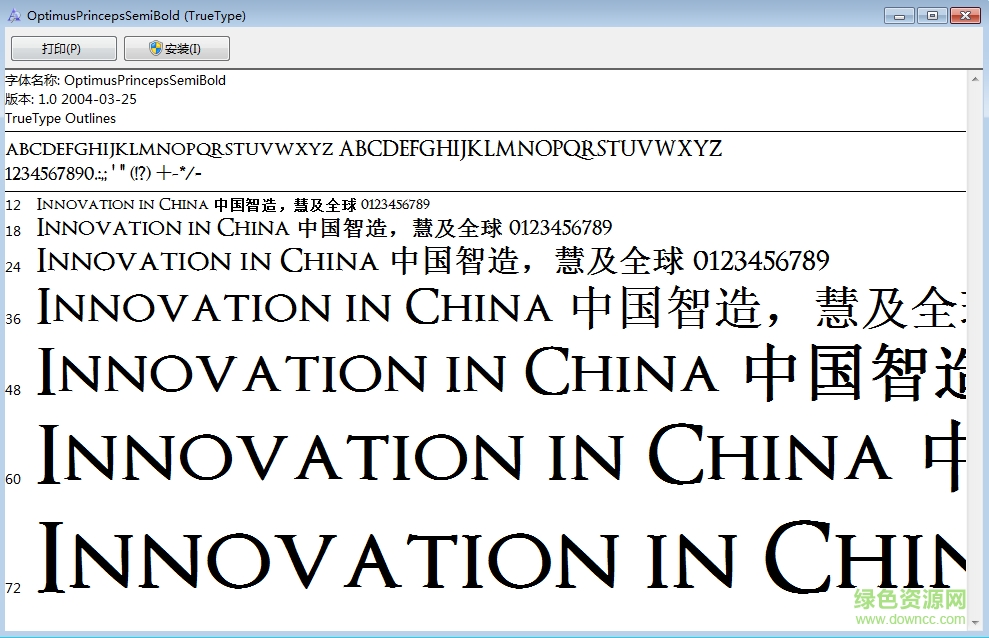
OptimusPrinceps SemiBold
optimusprinceps 字體是一款造型精簡(jiǎn)大氣的英文字體,深沉穩(wěn)重的字體不拖泥帶水,給人嚴(yán)謹(jǐn)莊嚴(yán)之感,適用于文書書寫、廣告設(shè)計(jì)等場(chǎng)合,綠色資源網(wǎng)誠(chéng)意推薦!
Optimusprinceps字體
optimusprincepssemibold半黑半粗,字體完整,支持中文繁簡(jiǎn)輸入,增加了文字設(shè)計(jì)的觀賞性和矚目性,對(duì)于平面設(shè)計(jì)、名片設(shè)計(jì)、廣告設(shè)計(jì)等場(chǎng)合很實(shí)用。